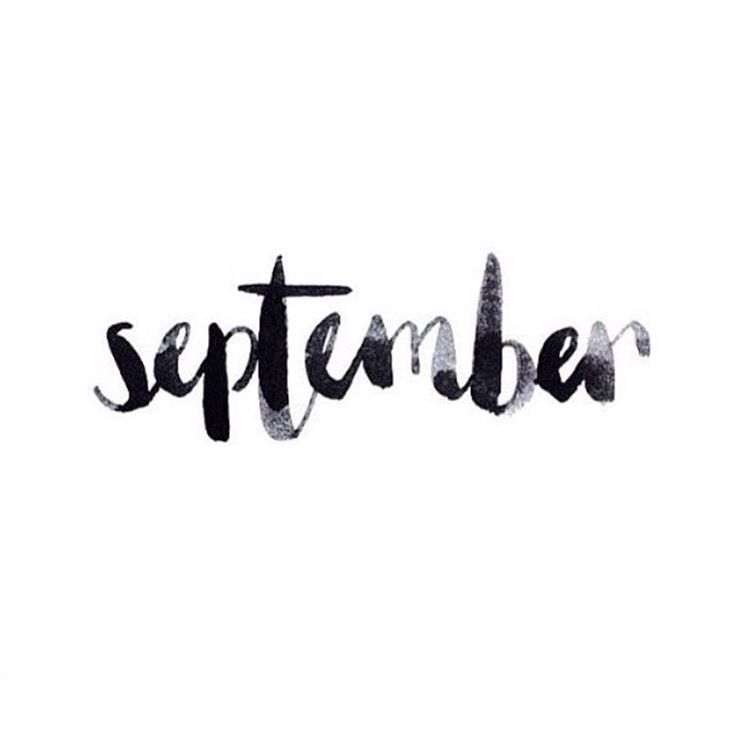
Красивым шрифтом сентябрь: Бесплатные шрифты на сентябрь | Креативы в Интернете
Бесплатные шрифты на сентябрь | Креативы в Интернете
За каждый прошедший час они происходят более 19.280 тыс. дизайнов в глобальном масштабе, так как предстоит проделать так много работы, в этом секторе необходимо иметь новые и разнообразные шрифты, и в конечном итоге типографика оказывается очень ценной во всех типах проектов, а именно то, что нельзя отрицать.
Как хороший шрифт повышает ценность проекта?
Удивительно, как простой шрифт или что-то вроде расстояние между буквами, способен напрямую влиять на отношение читателей к тому или иному дизайну.
Выбор подходящего шрифта обычно влияет на то, тратит ли читатель время на чтение некоторого контента, а это означает, что
По этой причине и в этой статье мы хотим показать вам источники, которые понравятся всем типам читателей, поэтому они не должны отсутствовать в вашей библиотеке.
Бесплатные шрифты сентябрь месяц
Коув Санс
Это бесплатный шрифт, имеет правильные кривые, поэтому он идеально подходит для заголовков, а также для дизайна логотипов. Он также имеет два типа толщины: жирный и светлый.
Хамурз
Peace sans
Это идеальный источник для разработки проектов с немного более простая и спокойная типографика. Его можно использовать как угодно, к тому же он совершенно бесплатный.
Плейлист бесплатно Источник
Он состоит из нарисованного вручную шрифта с стили сухой кисти. Он имеет три стиля: Орнамент, Надпись и Заглавные буквы, которые можно комбинировать, чтобы создать красивый и совершенный дизайн. Он может использовать этот шрифт для любых целей, независимо от того, является ли он личным или коммерческим, кроме того, что он идеально подходит для поздравительных открыток, свадебных приглашений, рисунков на футболках и т. д.
Portico
Нулевой шрифт
Является ли геометрический шрифт на основе сетки, это та же самая сетка, которая использовалась при разработке глифов «M» и «W».
Оказывается, он очень подходит для заголовков и постеров, а также для логотипов, он также полностью бесплатен и имеет лицензию на коммерческое использование.